Телетайпсеттинг: как перфолента передавала газетный набор на расстояние
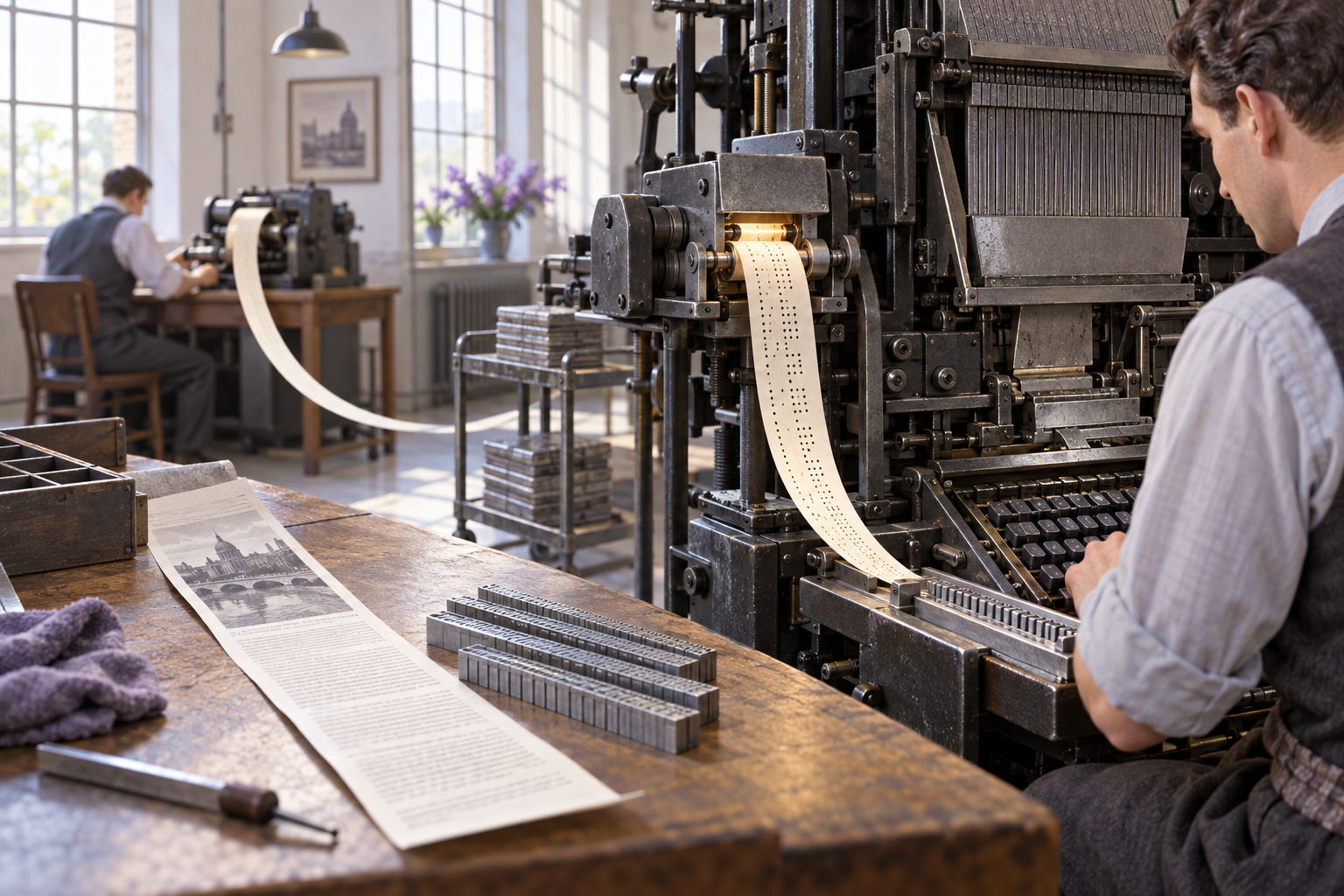
Телетайпсеттинг (Teletypesetter, TTS) позволял передавать редакционный текст в виде перфорированной бумажной ленты, а затем автоматически превращать её команды в набор на линотипе или приспособленной фотонаборной машине. Это была не просто дистанционная печать: в ленте кодировались буквы и команды набора. Разобрав процесс, можно понять, как готовить один текстовый оригинал для нескольких носителей и где проверять его перед выпуском.
Что именно передавала лента
Обычная телеграфная телеграмма сообщала текст, который затем кто-то должен был заново набрать на местной наборной машине. TTS добавлял к передаче машинно-читаемые команды: принимающая установка могла воспроизвести не только последовательность знаков, но и часть решений, необходимых для набора. Оператор в бюро новостного агентства печатал материал на перфораторе; отверстия в ленте задавали код. На другом конце линии реперфоратор мог создать копию ленты, а читатель ленты при наборной машине запускал команды в работу.
Важно не путать три вещи. Лента не была печатной формой и не содержала уже готовое изображение газетной страницы. Она несла закодированные символы и управляющую информацию. Линотип или совместимая фотонаборная машина выполняли собственно набор, а уже затем строки собирали в полосу и готовили к печати. Поэтому одинаковая лента могла дать разные готовые строки в газетах с разной шириной колонки, если на принимающей стороне настроить подходящие гарнитуру и кегль.
Технический обзор Национального бюро стандартов США описывает TTS-систему как введённую в 1932 году и указывает, что распространённая лента имела шесть кодовых дорожек и ширину 7/8 дюйма. Шесть отверстий дают 64 возможных комбинации, но код не сводился к «одна комбинация — одна буква»: часть команд меняла значение следующих кодов, переключая регистр или начертание. Поэтому точнее представить ленту как компактный поток символов и управляющих состояний. В том же обзоре отмечено, что TTS-копию можно было передавать по сетям связи, воспроизводить в удалённой редакции и подавать в адаптированные машины горячего набора или фотонабора (отчёт NBS на GovInfo).
Путь материала: от редактора до наборной машины
Практически процесс можно представить как цепочку из пяти ролей:
- **Автор или агентство** готовит текстовый оригинал и соблюдает редакционные правила.
- **Оператор перфоратора** вводит текст и команды в ленту. Его задача — передать материал в машиночитаемой форме, а не построить всю газетную полосу.
- **Канал связи и реперфоратор** доставляют сигнал в редакцию и воспроизводят ленту на месте. На некоторых этапах параллельно печаталась контрольная копия, понятная человеку.
- **Установка TTS при линотипе или фотонаборном аппарате** считывает код и выполняет допустимые команды набора.
- **Редактор и наборный цех** проверяют результат, собирают полосу, исправляют локальные особенности и передают форму дальше в производство.
Эта схема отделяла ввод текста от места, где физически изготовлялись строки. TIME в репортаже 1953 года описывал, как агентства передавали пробитую ленту, а редакция получала её копию и затем подавала в наборную машину. Издание также сообщало, что TTS применялся для агентских новостей и местных материалов (современный событиям репортаж TIME, 13 июля 1953 года). Это важный нюанс: технология была известна раньше, но широкое включение в агентские сети происходило постепенно. Дата появления системы и дата запуска конкретной сети — не одно и то же.
Почему удалённый набор был полезен газетам
Главная польза заключалась не в том, что машина «думала» за редактора. Повторяющийся набор можно было выполнять там, где он был нужен, не заставляя каждую редакцию заново печатать один и тот же материал. Для агентских сообщений это сокращало ручной повтор операций. Новостное бюро передавало текст в одной форме, а принимающая газета могла настроить машину под собственную колонку и выбранный размер набора.
Национальное бюро стандартов отдельно подчёркивало гибкость конечного производства: один и тот же исходный материал можно было набирать разными шрифтами и кеглями под разные ширины колонок. Лондонский музей показывает конкретный пример позднего применения: газетная машина Monarch в The Guardian могла работать вручную или через шестидорожечную ленту, проходившую через блок Fairchild Teletypesetter; этот экземпляр выпускал шрифт Royal Bold кеглей 8, 9 и 10 пунктов (карточка объекта London Museum). Деталь полезна для понимания границ автоматизации: поток текста мог быть общим, а типографические настройки — зависеть от конкретного производства.
TTS также менял организацию труда. С одной стороны, перфоратор и автоматический считыватель снимали часть повторяющегося набора с линотиписта. С другой — машина не решала за редакцию, какую новость поставить, что вырезать и как обработать локальную орфографию. Репортаж TIME обсуждал и опасения профессиональных союзов, и довод редакций о том, что выигранное время можно направить на местные материалы. Поэтому история TTS — не линейная история «машина заменила человека», а пример того, как автоматизация перераспределяла повторяемые операции и контроль.
Чего TTS не делал
Перфоленту легко принять за ранний цифровой файл страницы, но это неверно. Кодированное сообщение не описывало полностью геометрию полосы: изображения, рекламные блоки, заголовки, размеры колонок и окончательная композиция оставались отдельными задачами. Читатель ленты управлял совместимой машиной, но не превращал текст автоматически в готовую газетную страницу.